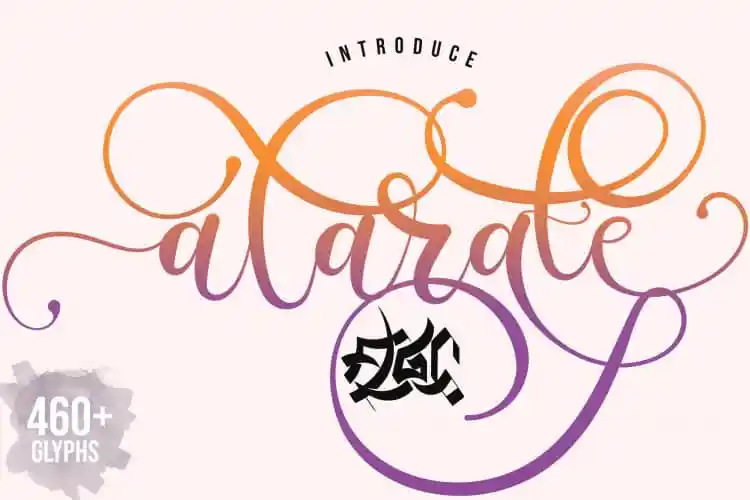
Alarate Script Font – Fonte Grátis
Alarate Script Font
A Alarate Script Font é uma ótima escolha para quem busca uma mistura elegante e delicada no seu design. Esta é uma tipografia moderna que inspira a escrita antiga, ideal para criar um toque feminino em seus projetos visuais. A fonte inclui belas travessas que adicionam um ar delicado às suas criações, tornando-a perfeita para design de convites, cartões de cumprimentos, materiais de marca e cards comerciais. Alarate é uma script feminino com estilo de escrita elegante, e seus caracteres decorativos garantem diversidade e originalidade. Além disso, a fonte oferece várias alternativas de caracteres, suportando ligaturas, alternativas contextualas, alternações estilizadas e conjuntos estilizados. Esses recursos permitem que você personalize suas criações de formas que vão além da simples escolha de uma fonte. Ideal para designers criativos que buscam uma maneira única de expressar seus projetos em convites de casamento, cartões de cumprimentos e materiais de marca, a Alarate Script Font é uma opção perfeita. Suas muitas possibilidades tornam-na versátil o suficiente para se adequar a um amplo espectro de aplicações designográficas. Não hesite em explorar a criatividade com essa fonte incrível, ela definitivamente vai adicionar um toque especial a seus projetos visuais.